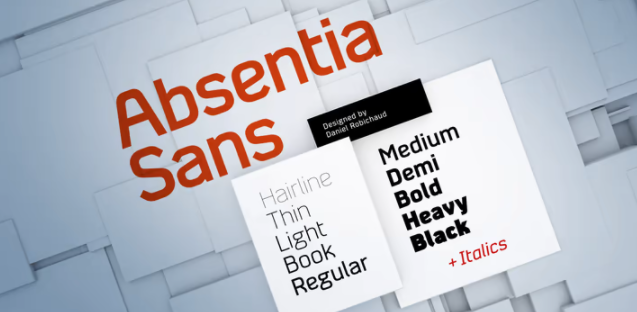
Absentia Sans - это геометрический шрифт без засечек с современной привлекательностью. Доступен в десяти весовых вариантах с соответствующим курсивом, семейство также включает два переменных шрифта. Построение глифов определяет их стиль: гармония линий, кривых и углов. Переходы штрихов с малым радиусом и наклонное завершение подчеркивают структурный подход и современную эстетику. И наоборот, изогнутый и конический терминал строчной буквы "l" - это кивок в сторону традиционной каллиграфии.
Этот уникальный стиль, а также характерное расположение таких букв, как "A", "Q" и "g", помогают семейству выделиться в толпе альтернативных вариантов без засечек. Его универсальность позволяет использовать его в самых разных областях - от индустриальных и футуристических до элегантных и изысканных. Тонко выверенный дизайн и большая высота x способствуют разборчивости при любом размере. Absentia Sans предлагает гибкое решение для современных типографских потребностей, для всех платформ, от страницы до экрана.